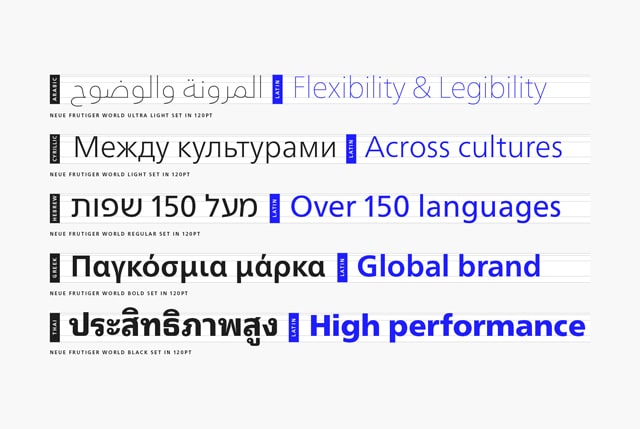
Monotype bringt Schriftfamilie Neue Frutiger World heraus
Der Technologie- und Schriftenanbieter Monotype stellte auf der “Adobe Max” in Los Angeles neue Features und Schriftdesigns vor. Neben der Schriftfamilie Neue Frutiger World präsentiert Monotype erweiterte Funktionen der Font-Management-Plattform Mosaic.
Die Neue Frutiger World ist eine globale Schriftfamilie, die konzipiert ist für Branding, Informationsdesign und Leitsysteme, bis hin zum Editorial Design. Die zehnschnittige Schriftfamilie (+ Kursive) unterstützt insgesamt 150 Sprachen und Schreibsysteme, darunter Griechisch, Kyrillisch, Georgisch, Armenisch, Hebräisch, Arabisch, Thai und Vietnamesisch. Ebenfalls neu sind optionale asiatische Ergänzungen, basierend auf der Frutiger und abgestimmt auf die Neue Frutiger World: M XiangHe Hei für Chinesisch, Seol Sans für Koreanisch und Tazugane Info für Japanisch.